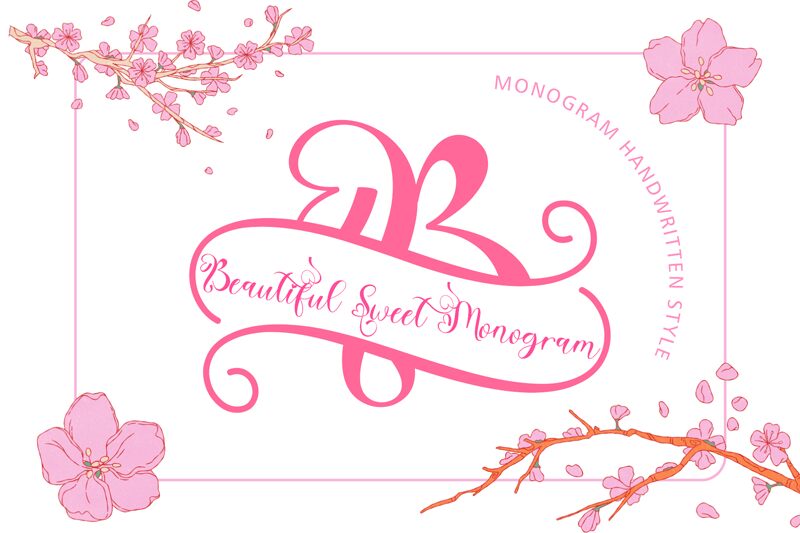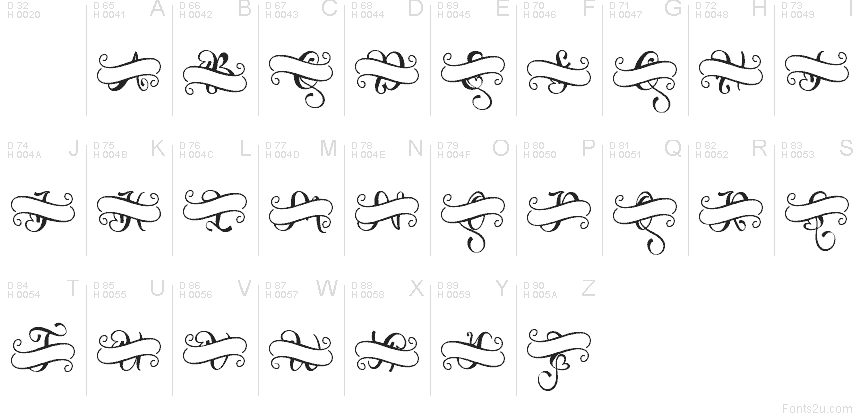
Sweet Monogram Only
Sweet Monogram Only de Yoga Letter es una tipografía display decorativa gratuita que cuenta con trazos caligráficos fluidos y un marco estilo monograma. Sus largas líneas curvas envuelven un centro abierto, lo que le aporta un aspecto ornamental y artesanal, ideal para usar como acento visual más que para texto principal.
Sweet Monogram Only es perfecta para invitaciones de boda, logotipos personales, packaging de boutiques, papelería, etiquetas de regalo y gráficos de redes sociales donde se requiera un acabado elegante en una sola inicial o monograma corto. Su contorno ondulado y sus remates extendidos también la hacen muy útil para etiquetas, logotipos de marca y sellos decorativos que buscan un toque refinado y hecho a medida.